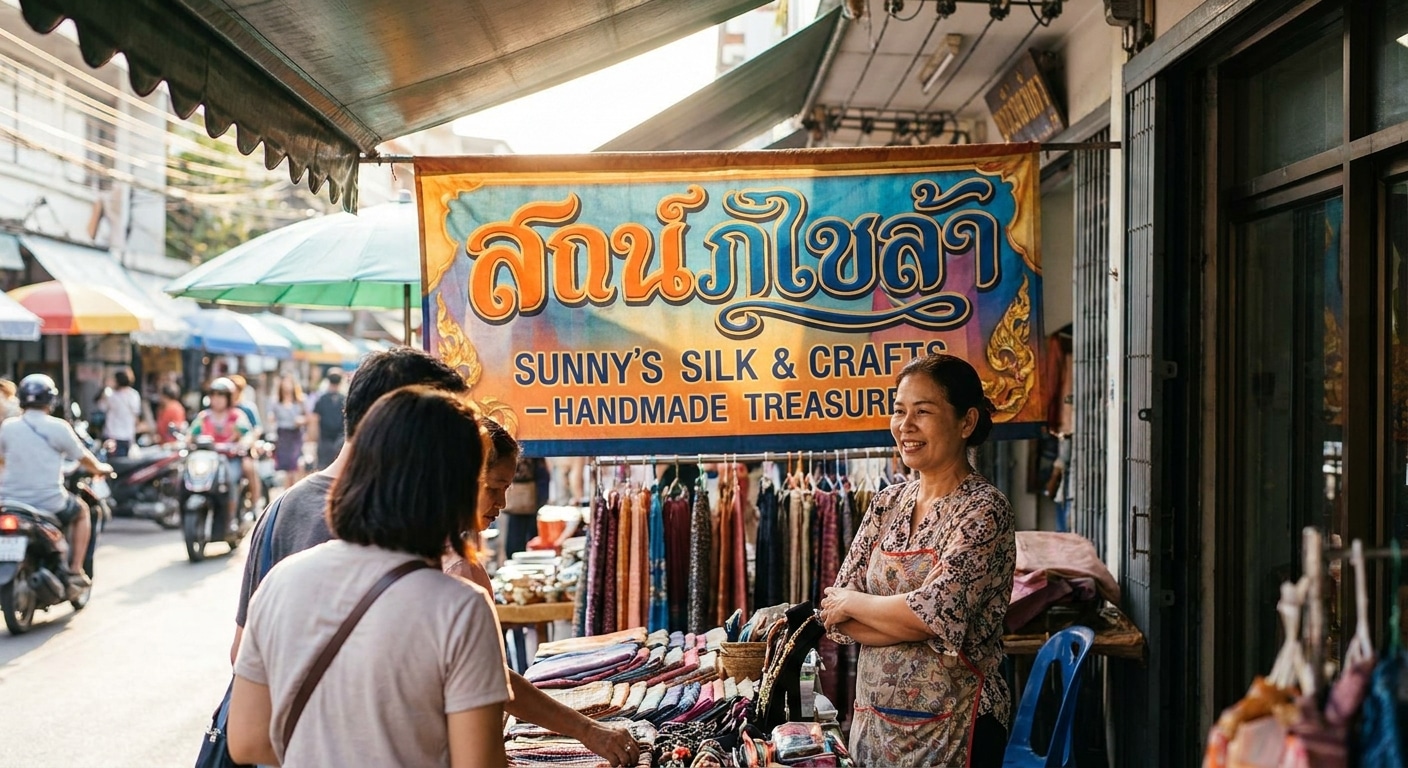
เทคนิคเลือกฟอนต์ทำป้ายโฆษณา ดึงดูดลูกค้า สะดุดตาแต่ไกล
การเลือกใช้ เทคนิคเลือกฟอนต์ทำป้ายโฆษณา ดึงดูดลูกค้า สะดุดตาแต่ไกล เป็นองค์ประกอบสำคัญที่ส่งผลโดยตรงต่อประสิทธิภาพในการสื่อสารกับกลุ่มเป้าหมาย ป้ายโฆษณาที่ออกแบบมาอย่างดีไม่เพียงแต่ให้ข้อมูล แต่ยังทำหน้าที่เป็นเครื่องมือสร้างการรับรู้และดึงดูดสายตาของผู้คนให้หยุดมอง โดยเฉพาะในสภาวะแวดล้อมที่มีการแข่งขันสูง การเลือกฟอนต์ที่เหมาะสมจึงเป็นกุญแจสำคัญในการสร้างความแตกต่างและทำให้แบรนด์เป็นที่น่าจดจำ
สรุปประเด็นสำคัญในการเลือกฟอนต์
- ความชัดเจนมาก่อน: เลือกฟอนต์ที่อ่านง่ายจากระยะไกล โดยเฉพาะฟอนต์ประเภท Sans-serif ซึ่งเหมาะกับป้ายกลางแจ้งและป้ายที่ต้องมองเห็นในเวลาอันสั้น
- จำกัดจำนวนฟอนต์: การใช้ฟอนต์ไม่เกิน 2 รูปแบบบนป้ายเดียวช่วยสร้างความเป็นระเบียบและทำให้ข้อความไม่สับสน ง่ายต่อการจดจำ
- ขนาดและน้ำหนักคือหัวใจ: ปรับขนาดและความหนาของฟอนต์เพื่อสร้างลำดับความสำคัญของข้อมูล ทำให้ส่วนที่สำคัญที่สุด เช่น โปรโมชั่นหรือชื่อแบรนด์ โดดเด่นที่สุด
- สะท้อนตัวตนแบรนด์: ฟอนต์แต่ละแบบให้อารมณ์และความรู้สึกที่แตกต่างกัน การเลือกฟอนต์ที่สอดคล้องกับบุคลิกของแบรนด์จะช่วยเสริมสร้างภาพลักษณ์ให้แข็งแกร่งขึ้น
- ทดสอบก่อนใช้งานจริง: ควรมีการทดสอบการมองเห็นป้ายจากระยะทางและความเร็วต่างๆ ที่กลุ่มเป้าหมายจะมองเห็น เพื่อให้แน่ใจว่าข้อความสามารถสื่อสารได้อย่างมีประสิทธิภาพ
ความสำคัญของการเลือกฟอนต์สำหรับป้ายโฆษณา
ในโลกของการตลาดที่เต็มไปด้วยสิ่งเร้าทางสายตา ป้ายโฆษณาทำหน้าที่เป็นด่านแรกในการสร้างปฏิสัมพันธ์ระหว่างแบรนด์และลูกค้าเป้าหมาย โดยเฉพาะสำหรับธุรกิจ SME ป้ายหน้าร้าน ป้ายไวนิล หรือป้ายสแตนดี้ ถือเป็นเครื่องมือทางการตลาดที่ทรงพลังและเข้าถึงง่ายที่สุด อย่างไรก็ตาม ประสิทธิผลของป้ายเหล่านี้ขึ้นอยู่กับองค์ประกอบหลายอย่าง และ “ฟอนต์” หรือรูปแบบตัวอักษร คือหนึ่งในปัจจัยที่มักถูกมองข้าม แต่กลับมีความสำคัญอย่างยิ่งยวด
กลุ่มเป้าหมายส่วนใหญ่มองเห็นป้ายโฆษณาในขณะที่กำลังเคลื่อนที่ เช่น ขับรถหรือเดินผ่าน ซึ่งหมายความว่าพวกเขามีเวลาเพียง 1-3 วินาทีในการรับสาร หากฟอนต์ที่ใช้มีความซับซ้อน อ่านยาก หรือบางเกินไป ข้อความนั้นก็จะสูญเปล่าทันที การเลือกฟอนต์จึงไม่ใช่แค่เรื่องของความสวยงาม แต่เป็นเรื่องของหลักการสื่อสารที่ต้องคำนึงถึง ความชัดเจน (Legibility) และ ความง่ายในการอ่าน (Readability) เป็นอันดับแรก ฟอนต์ที่ดีจะช่วยให้ผู้คนสามารถประมวลผลข้อมูลได้อย่างรวดเร็วและแม่นยำ นำไปสู่การจดจำแบรนด์และอาจกระตุ้นให้เกิดการตัดสินใจซื้อในที่สุด
ฟอนต์บนป้ายโฆษณาเปรียบเสมือน “น้ำเสียง” ของแบรนด์ หากเลือกได้ถูกต้อง จะสามารถสื่อสารบุคลิกภาพ ความน่าเชื่อถือ และดึงดูดกลุ่มเป้าหมายที่ใช่ได้อย่างมีประสิทธิภาพ
ประเภทฟอนต์ที่ใช่: เลือกอย่างไรให้ป้ายโดดเด่น
การทำความเข้าใจประเภทของฟอนต์และลักษณะเฉพาะของแต่ละแบบเป็นขั้นตอนแรกในการเลือกฟอนต์ที่เหมาะสมกับป้ายโฆษณา ฟอนต์แต่ละกลุ่มมีจุดเด่นและข้อจำกัดที่แตกต่างกัน การเลือกใช้ให้ถูกกับบริบทและวัตถุประสงค์จึงเป็นสิ่งจำเป็น
ฟอนต์ Sans-serif: ตัวเลือกอันดับหนึ่งเพื่อความชัดเจน
ฟอนต์ประเภท Sans-serif หรือฟอนต์ “ไม่มีหัว” คือกลุ่มฟอนต์ที่ไม่มีเส้นขีดเล็กๆ (Serif) ประดับอยู่ที่ปลายตัวอักษร ทำให้มีรูปลักษณ์ที่เรียบง่าย ทันสมัย และสะอาดตา ด้วยลักษณะดังกล่าว ฟอนต์ Sans-serif จึงได้รับการยอมรับอย่างกว้างขวางว่าเป็นตัวเลือกที่ดีที่สุดสำหรับป้ายโฆษณา โดยเฉพาะป้ายที่ต้องการให้อ่านได้จากระยะไกลหรือในขณะเคลื่อนที่
ข้อดีหลักของฟอนต์กลุ่มนี้คือความชัดเจนของรูปทรงตัวอักษรแต่ละตัว ซึ่งไม่ถูกรบกวนด้วยรายละเอียดเล็กๆ น้อยๆ ทำให้สายตาสามารถจับใจความได้ง่ายและรวดเร็ว เหมาะอย่างยิ่งสำหรับป้ายหน้าร้าน, ป้ายโฆษณาบนทางด่วน, ป้ายบิลบอร์ด, และสื่อประชาสัมพันธ์ที่ต้องการสื่อสารข้อความสำคัญในเวลาอันสั้น แบรนด์ที่เกี่ยวข้องกับเทคโนโลยี, นวัตกรรม, หรือสินค้าที่ต้องการสื่อถึงความทันสมัยมักนิยมใช้ฟอนต์ประเภทนี้เพื่อสะท้อนภาพลักษณ์ของตน ตัวอย่างฟอนต์ในกลุ่มนี้ที่นิยมใช้ได้แก่ Lucida Sans หรือฟอนต์ตระกูลหัวกลมที่มีความหนา
ฟอนต์ Serif: ใช้เมื่อต้องการความน่าเชื่อถือ
ฟอนต์ Serif หรือฟอนต์ “มีหัว” เป็นฟอนต์ที่มีเส้นขีดตกแต่งเล็กๆ อยู่ที่ปลายตัวอักษร ซึ่งเป็นรูปแบบดั้งเดิมที่พบเห็นได้บ่อยในสื่อสิ่งพิมพ์ เช่น หนังสือพิมพ์หรือนิตยสาร เส้นขีดเหล่านี้ช่วยนำสายตาในการอ่านข้อความยาวๆ บนหน้ากระดาษ ฟอนต์ประเภทนี้มักให้ความรู้สึกถึงความเป็นทางการ, ความน่าเชื่อถือ, ความคลาสสิก และความเป็นมืออาชีพ
อย่างไรก็ตาม สำหรับการใช้งานบนป้ายโฆษณาระยะไกล ฟอนต์ Serif อาจไม่ใช่ตัวเลือกที่ดีที่สุดเสมอไป เนื่องจากเส้นขีดเล็กๆ อาจทำให้ตัวอักษรดูเบลอหรือไม่คมชัดเมื่อมองจากระยะไกลหรือในสภาพแสงน้อย แต่ก็สามารถนำมาใช้ได้ในบางกรณี เช่น ป้ายชื่อคลินิก, สำนักงานกฎหมาย, หรือแบรนด์สินค้าสุขภาพที่ต้องการสร้างความรู้สึกน่าเชื่อถือและมั่นคง ควรเลือกใช้เฉพาะกับข้อความสั้นๆ หรือชื่อแบรนด์ และต้องแน่ใจว่าขนาดใหญ่และหนาเพียงพอที่จะมองเห็นได้ชัดเจน
ฟอนต์เฉพาะทาง: ตัวกลมและลายมือ
นอกเหนือจากสองประเภทหลักแล้ว ยังมีฟอนต์ที่มีลักษณะเฉพาะตัว เช่น ฟอนต์ตัวกลม (Rounded) หรือฟอนต์ลายมือ (Handwriting/Script) ฟอนต์เหล่านี้สามารถสร้างเอกลักษณ์และสื่อสารอารมณ์ได้เป็นอย่างดี ฟอนต์ตัวกลมมักให้ความรู้สึกเป็นมิตร, อบอุ่น, และเข้าถึงง่าย จึงเหมาะกับธุรกิจประเภทคาเฟ่, ร้านเบเกอรี่, สินค้าโฮมเมด, หรือแบรนด์ที่เกี่ยวข้องกับเด็ก ส่วนฟอนต์ลายมือสามารถสร้างความรู้สึกหรูหรา, เป็นกันเอง, หรือมีความเป็นศิลปะ ขึ้นอยู่กับรูปแบบของลายเส้น
ข้อควรระวังในการใช้ฟอนต์กลุ่มนี้คือ ควรใช้เป็นส่วนเสริมเพื่อสร้างจุดเด่น เช่น ใช้กับชื่อแบรนด์หรือคำโปรยสั้นๆ ไม่ควรใช้กับข้อความหลักหรือข้อมูลสำคัญ เนื่องจากมักจะอ่านได้ยากกว่าฟอนต์มาตรฐาน โดยเฉพาะเมื่อต้องมองจากระยะไกล
ฟอนต์ที่ควรหลีกเลี่ยงสำหรับป้ายระยะไกล
เพื่อประสิทธิภาพสูงสุดในการสื่อสาร มีฟอนต์บางประเภทที่ควรหลีกเลี่ยงโดยเด็ดขาดสำหรับการทำป้ายโฆษณาที่ต้องการการมองเห็นจากระยะไกล:
- ฟอนต์ลายมือที่หวัดหรือต่อกัน (Script): แม้จะสวยงาม แต่ก็อ่านได้ยากและใช้เวลาประมวลผลนาน
- ฟอนต์ที่มีความบางหรือแคบมาก (Thin/Condensed): ตัวอักษรจะจมหายไปกับพื้นหลังเมื่อมองจากระยะไกล
- ฟอนต์ที่มีการตกแต่งเยอะ (Decorative/Display): รายละเอียดที่ซับซ้อนจะรบกวนการอ่านและทำให้ข้อความไม่ชัดเจน
กฎทองของการออกแบบ: น้อยแต่มาก ทรงพลัง
หลักการ “Less is More” หรือ “น้อยแต่มาก” เป็นแนวคิดที่ใช้ได้ผลเสมอในการออกแบบป้ายโฆษณา การใช้ฟอนต์หลากหลายประเภทบนป้ายเดียวกันอาจดูน่าสนใจในตอนแรก แต่ในความเป็นจริงแล้วกลับสร้างความสับสนและทำให้ป้ายดูไม่เป็นมืออาชีพ การจำกัดจำนวนฟอนต์ที่ใช้เป็นเทคนิคสำคัญที่ช่วยให้การสื่อสารมีความชัดเจนและทรงพลังมากขึ้น
โดยทั่วไปแล้ว แนะนำให้ใช้ฟอนต์บนป้ายโฆษณาไม่เกิน 2 รูปแบบ การทำเช่นนี้ช่วยสร้างความเป็นระเบียบและลำดับชั้นของข้อมูลได้อย่างชัดเจน โดยสามารถแบ่งการใช้งานได้ดังนี้:
- ฟอนต์หลัก (Primary Font): ใช้สำหรับหัวข้อหลัก, ชื่อแบรนด์, หรือข้อความที่สำคัญที่สุดที่ต้องการดึงดูดสายตาเป็นอันดับแรก ควรเป็นฟอนต์ที่มีความโดดเด่น, หนา, และอ่านง่าย
- ฟอนต์รอง (Secondary Font): ใช้สำหรับข้อความย่อย, รายละเอียดเพิ่มเติม, หรือข้อมูลติดต่อ ควรเป็นฟอนต์ที่เรียบง่าย, อ่านง่ายแม้จะมีขนาดเล็กกว่า และเข้ากันได้ดีกับฟอนต์หลัก
การจำกัดจำนวนฟอนต์ไม่เพียงแต่ช่วยเรื่องความสวยงามและความเป็นระเบียบ แต่ยังช่วยให้ผู้บริโภคจดจำเอกลักษณ์ของแบรนด์ได้ง่ายขึ้น เมื่อเห็นการใช้ฟอนต์คู่เดิมซ้ำๆ ในสื่อต่างๆ ก็จะเกิดการเชื่อมโยงและสร้างการรับรู้แบรนด์ที่แข็งแกร่งในระยะยาว
การจับคู่ฟอนต์อย่างมืออาชีพ
การเลือกฟอนต์ 2 แบบมาใช้งานร่วมกันต้องอาศัยหลักการเพื่อให้เกิดความกลมกลืนและน่าสนใจ เทคนิคหนึ่งที่นิยมใช้คือการเลือกฟอนต์ที่มาจาก “คลาส” หรือตระกูลเดียวกัน เช่น การใช้ฟอนต์ Lucida Sans คู่กับ Lucida ซึ่งมีความคล้ายคลึงกันในโครงสร้างแต่แตกต่างกันที่รายละเอียด (มีหัวกับไม่มีหัว) ทำให้เกิดความต่อเนื่องแต่ยังคงแยกแยะลำดับความสำคัญได้ หรืออีกวิธีคือการใช้ฟอนต์ตัวเดียวแต่ปรับเปลี่ยนน้ำหนัก (Weight) เช่น ใช้ฟอนต์แบบหนา (Bold) สำหรับหัวข้อ และใช้น้ำหนักปกติ (Regular) สำหรับเนื้อหา ซึ่งเป็นวิธีที่ปลอดภัยและได้ผลดีเสมอ
ขนาดและน้ำหนัก: สร้างลำดับชั้นทางสายตา
หลังจากเลือกประเภทและจำนวนฟอนต์ได้แล้ว ปัจจัยต่อไปที่มีความสำคัญไม่แพ้กันคือ “ขนาด” และ “น้ำหนัก” ของฟอนต์ สองสิ่งนี้เป็นเครื่องมือหลักในการสร้างลำดับชั้นทางสายตา (Visual Hierarchy) ซึ่งเป็นการชี้นำสายตาของผู้ชมให้มองไปยังส่วนที่สำคัญที่สุดก่อน แล้วจึงไล่ไปยังส่วนที่มีความสำคัญรองลงมา
การกำหนดขนาดที่เหมาะสมกับระยะการมองเห็น
ขนาดของฟอนต์ต้องใหญ่พอที่จะมองเห็นได้อย่างชัดเจนจากระยะทางที่คาดหวัง สำหรับป้ายโฆษณาริมถนนที่ผู้คนมองเห็นขณะขับรถด้วยความเร็วสูง ขนาดของตัวอักษรต้องใหญ่เป็นพิเศษ ในขณะที่ป้ายหน้าร้านสำหรับคนเดินเท้าอาจใช้ขนาดที่เล็กลงมาได้ หลักการง่ายๆ คือ ยิ่งระยะการมองเห็นไกลเท่าไหร่ ขนาดตัวอักษรก็ต้องใหญ่ขึ้นเท่านั้น
นอกจากนี้ การใช้น้ำหนักของฟอนต์ (เช่น Regular, Bold, Extra Bold) ยังช่วยเน้นย้ำข้อความสำคัญได้เป็นอย่างดี ข้อความที่เป็นจุดขายหลัก เช่น “ลด 50%!” หรือ “เปิดใหม่!” ควรใช้ฟอนต์ตัวหนา (Bold) เพื่อให้สะดุดตาและดึงดูดความสนใจได้ทันที การไล่ระดับขนาดและความหนาจาก ใหญ่/หนา → กลาง/ปกติ → เล็ก/บาง จะช่วยจัดระเบียบข้อมูลบนป้ายได้อย่างมีประสิทธิภาพ
เทคนิคการจัดวางและเว้นวรรค
การเว้นระยะห่างที่เหมาะสมก็เป็นส่วนหนึ่งของการสร้างความชัดเจน ระยะห่างระหว่างบรรทัด (Line Height) และระยะห่างรอบๆ ข้อความ (Padding หรือ White Space) ควรมีอย่างเพียงพอ ไม่ทำให้ตัวอักษรดูอึดอัดหรือติดกันเป็นพรืด การมีพื้นที่ว่างรอบๆ จะช่วยให้ข้อความโดดเด่นขึ้นมาและทำให้สายตาสามารถโฟกัสที่เนื้อหาได้ง่ายขึ้น ส่งผลให้การอ่านสบายตาและรวดเร็ว โดยเฉพาะเมื่อมองจากระยะไกล
จิตวิทยาของฟอนต์: สื่อสารตัวตนแบรนด์ผ่านตัวอักษร
ฟอนต์ไม่ได้เป็นเพียงตัวอักษรสำหรับอ่าน แต่ยังเป็นองค์ประกอบทางภาพที่สามารถกระตุ้นอารมณ์และความรู้สึกได้โดยไม่รู้ตัว การเลือกฟอนต์จึงเป็นการตัดสินใจเชิงกลยุทธ์ที่สามารถสะท้อนบุคลิกและตัวตนของแบรนด์ (Brand Personality) ไปยังกลุ่มเป้าหมายได้อย่างแม่นยำ การทำความเข้าใจจิตวิทยาเบื้องหลังฟอนต์แต่ละประเภทจะช่วยให้สามารถเลือกใช้ได้อย่างเหมาะสมกับภาพลักษณ์และกลุ่มลูกค้า
| ประเภทฟอนต์ | ความรู้สึกที่สื่อสาร | เหมาะกับป้ายประเภทไหน |
| Sans-serif (หนา) | ทันสมัย, แข็งแกร่ง, ทรงพลัง, ชัดเจน | ป้ายโปรโมชั่น, ป้ายร้านค้าปลีก, แบรนด์เทคโนโลยี, สินค้าแฟชั่น, ป้ายที่ต้องการความโดดเด่น |
| Serif | น่าเชื่อถือ, เป็นทางการ, คลาสสิก, มืออาชีพ | ป้ายสถาบันการเงิน, สินค้าสุขภาพ, สำนักงานกฎหมาย, แบรนด์ที่เน้นประวัติศาสตร์และความดั้งเดิม |
| ตัวกลม / Whimsical | เป็นมิตร, สนุกสนาน, อบอุ่น, เข้าถึงง่าย | ป้ายร้านคาเฟ่, เบเกอรี่, สินค้าสำหรับเด็ก, ร้านขายของแฮนด์เมด, ธุรกิจที่เน้นความเป็นกันเอง |
| Script / ลายมือ | หรูหรา, อ่อนโยน, เป็นส่วนตัว, มีศิลปะ | ป้ายร้านเสริมสวย, สปา, แบรนด์เครื่องประดับ, การ์ดเชิญ (ใช้เป็นส่วนตกแต่ง ไม่ใช่ข้อความหลัก) |
การเลือกฟอนต์ให้สอดคล้องกับกลุ่มเป้าหมายก็เป็นสิ่งสำคัญเช่นกัน หากกลุ่มเป้าหมายคือเด็กหรือวัยรุ่น การใช้ฟอนต์ตัวกลมหรือฟอนต์ที่มีลูกเล่นอาจดึงดูดความสนใจได้ดีกว่า ในทางกลับกัน หากกลุ่มเป้าหมายคือผู้สูงอายุหรือกลุ่มลูกค้าองค์กร การใช้ฟอนต์ที่ดูเป็นทางการและอ่านง่ายอย่าง Sans-serif หรือ Serif จะเหมาะสมกว่า การพิจารณาบริบทเหล่านี้จะช่วยให้การสื่อสารของแบรนด์มีประสิทธิภาพและสร้างผลกระทบเชิงบวกต่อการรับรู้ของลูกค้าได้สูงสุด
เทคนิคเสริมเพื่อเพิ่มพลังดึงดูดให้ป้ายโฆษณา
นอกเหนือจากหลักการพื้นฐานในการเลือกประเภท ขนาด และจำนวนฟอนต์แล้ว ยังมีเทคนิคเสริมอื่นๆ ที่จะช่วยเพิ่มพลังดึงดูดและทำให้ป้ายโฆษณามีความโดดเด่นสะดุดตามากยิ่งขึ้น
- สีและคอนทราสต์ (Color and Contrast): การเลือกสีของฟอนต์และสีพื้นหลังเป็นปัจจัยสำคัญอย่างยิ่ง ควรเลือกใช้สีที่มีคอนทราสต์สูง เช่น ตัวอักษรสีเข้มบนพื้นหลังสีอ่อน หรือตัวอักษรสีอ่อนบนพื้นหลังสีเข้ม เพื่อให้สามารถอ่านข้อความได้ง่ายและชัดเจนจากระยะไกล การใช้สีประจำแบรนด์ (Brand Identity Colors) กับตัวอักษรเป็นวิธีที่ดีในการสร้างการจดจำ แต่ต้องแน่ใจว่าสีนั้นโดดเด่นเพียงพอเมื่ออยู่บนพื้นหลังที่เลือก
- การเน้นจุดเด่นด้วยสีและน้ำหนัก: สามารถใช้เทคนิคผสมผสานระหว่างการทำตัวหนา (Bold) และการใช้สีที่แตกต่าง (Highlight Color) เพื่อเน้นคำหรือข้อความที่สำคัญที่สุดบนป้าย เช่น ราคาพิเศษ, คำว่า “ฟรี”, หรือเปอร์เซ็นต์ส่วนลด วิธีนี้จะช่วยชี้นำสายตาของผู้ชมไปยังจุดที่ต้องการสื่อสารได้ทันที
- การทดสอบในสถานการณ์จริง: ก่อนที่จะตัดสินใจผลิตป้ายจริง ควรมีการออกแบบตัวอย่างและนำไปทดสอบในสภาพแวดล้อมจริง ลองมองจากระยะทางต่างๆ ที่ลูกค้าจะเห็น หรือลองจำลองการมองเห็นขณะขับรถผ่าน เพื่อประเมินว่าฟอนต์และข้อความทั้งหมดสามารถอ่านได้ง่ายและชัดเจนตามที่คาดหวังไว้หรือไม่ การทดสอบนี้จะช่วยลดความผิดพลาดและทำให้มั่นใจได้ว่าป้ายที่ผลิตออกมาจะทำงานได้อย่างมีประสิทธิภาพสูงสุด
บทสรุปและแนวทางการนำไปใช้
การใช้ เทคนิคเลือกฟอนต์ทำป้ายโฆษณา ดึงดูดลูกค้า สะดุดตาแต่ไกล ไม่ใช่เพียงเรื่องของความสวยงาม แต่เป็นศาสตร์และศิลป์ที่ผสมผสานหลักการออกแบบเข้ากับจิตวิทยาการตลาด เพื่อสร้างการสื่อสารที่มีประสิทธิภาพสูงสุดในเวลาที่จำกัด การให้ความสำคัญกับความชัดเจน (Legibility) และความอ่านง่าย (Readability) โดยเลือกใช้ฟอนต์ Sans-serif เป็นหลัก, จำกัดจำนวนฟอนต์ไม่เกิน 2 แบบ, สร้างลำดับชั้นด้วยขนาดและน้ำหนัก, และเลือกฟอนต์ที่สะท้อนตัวตนของแบรนด์ จะช่วยให้ป้ายโฆษณาไม่ว่าจะเป็นป้ายหน้าร้าน ป้ายไวนิล หรือป้ายสแตนดี้ สามารถทำหน้าที่ดึงดูดสายตาและสื่อสารข้อความสำคัญไปยังกลุ่มเป้าหมายได้อย่างแม่นยำและน่าจดจำ